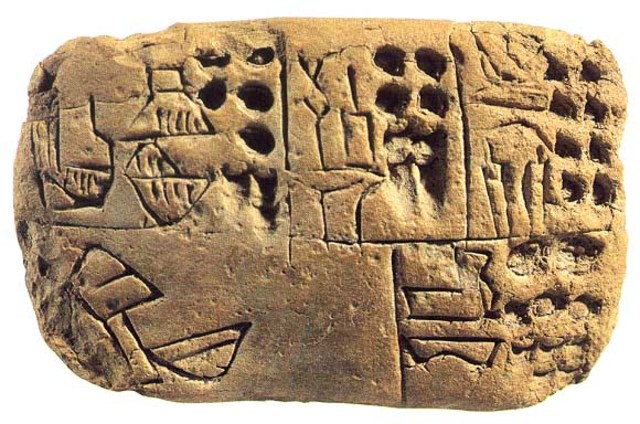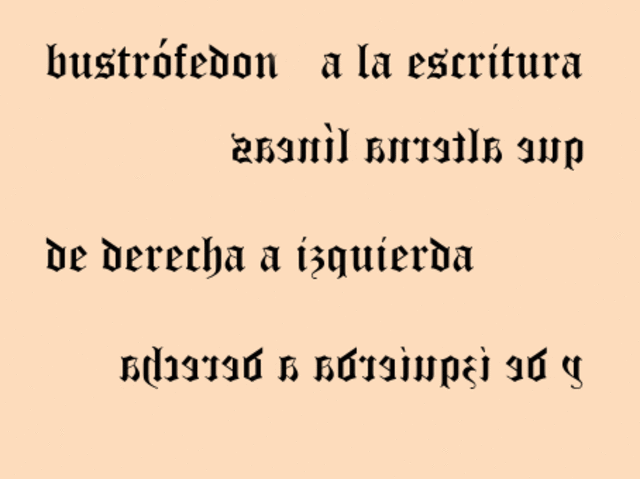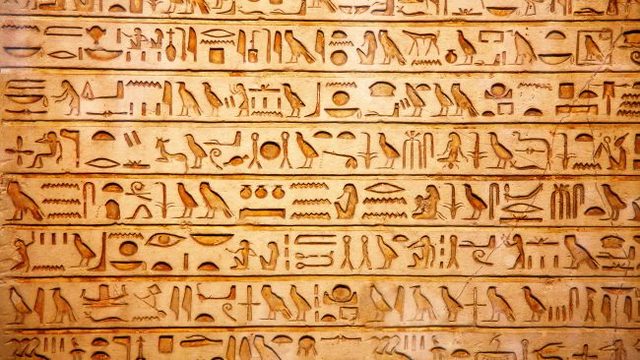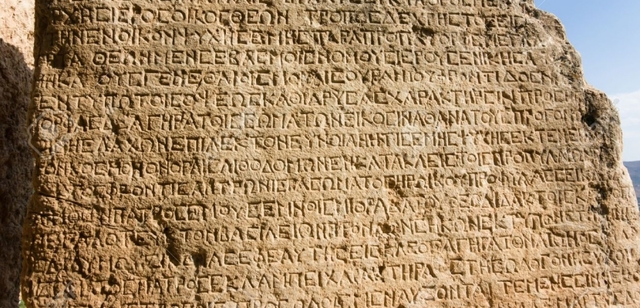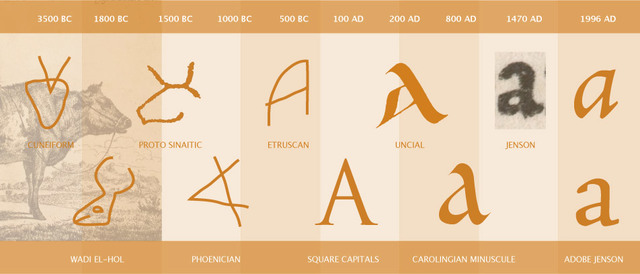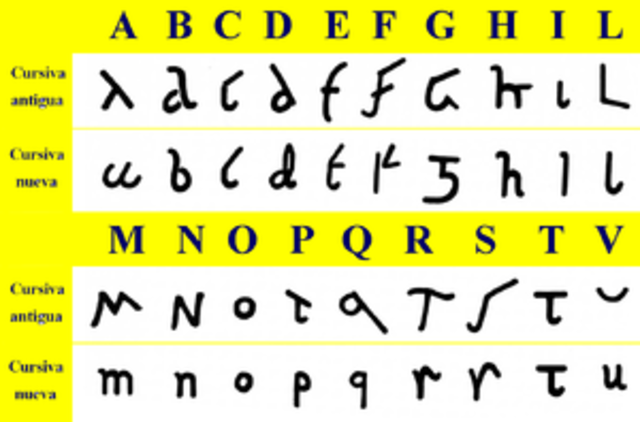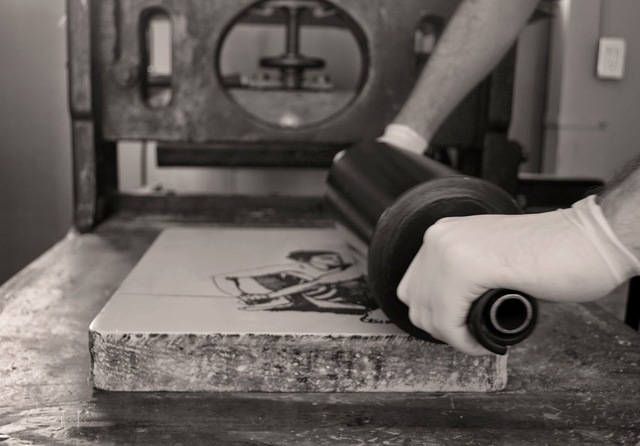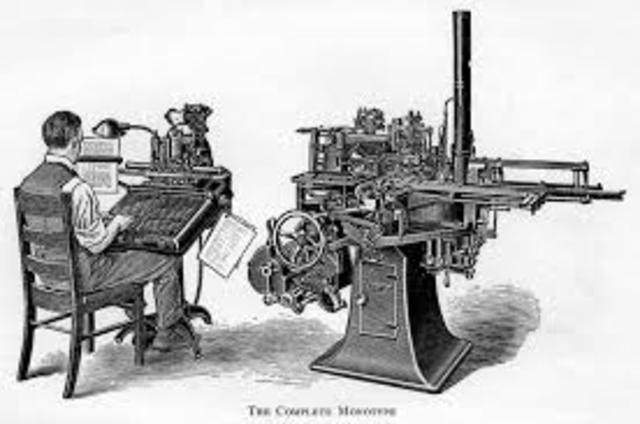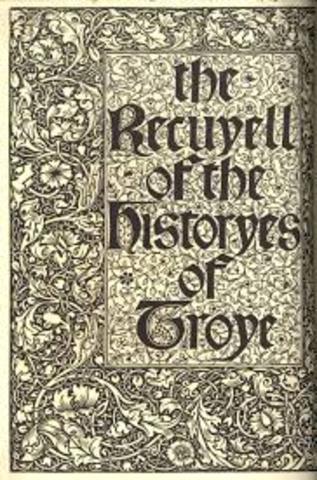
Se basa en pictogramas y se emplea con los incas y los antiguos egipcios. cada pictograma representaba un símbolo. se escribe de derecha a izquierda, se utilizaban ideogramas
se brinda un símbolo a cada palabra, paso palabras abstractas y finalmente quedo como caligrafía del pequeño sello. en el año 1600 impartieron el alfabeto latino.
se relacionaba a escribir columnas inclinadas, pero con el pasar del tiempo se convirtió en una escritura de izquierda a derecha y se cambiaron a los signos. Los escritos cuneiformes desaparecieron en los siglos VI Y VII ac.
La escritura de griega antiguo la escribían en bustrófedon, esta escritura añadió los signos de puntuación lo cual hizo que se desapareciera la escritura de bustrófedon.
Este alfabeto lo utilizaban para la escritura de seis lenguas eslavas, pedro el grande decreto el uso de las letras occidentalizadas y fueron adoptados por el resto de las lenguas y se establece mas 50 lenguas diferentes en Rusia.
se construye con el alfabeto griego y se divulgo por el imperio. Los romanos siempre trataban de emplear siete de sus letras como números básicos porque cada letra representaba un valor numérico.
Consta de 52 letras y 10 números así como símbolos, signos de puntuación y distintas lenguas, las letras de caja baja se inician con las letras mayúsculas.
La transformacion del arameo fue desde el fenicio, el arameo es un lenguaje semitico que se remplazo a finales del VI a.c, suplantado por la escritura hebrea.
Los primeros libros de bloque se imprimieron con un sello de mano y tinta color sepia o gris, que luego sería reemplazada por la tinta negra. Después de imprimir el texto y las ilustraciones, estas se coloreaban a mano con la misma técnica que se aplicaba en los manuscritos góticos.
se imprimió el primer libro en inglés bajo el título de Recuyell of th Historyes of troye del Autot: Raold le Fèvre.
Supuso la fusión del arte y la industria para la
producción de carteles y cromos en color para libros. -
Era un teclado similar al de una barra de escribir con una barra metálica la maquina coloca matrices de latón en una linea y después se difunden.
hace fundición de las letras en plomo y las plasma en una pagina, lo cual le permite la corrección de caracteres individuales.
En el Antiguo Egipto se escribía sobre papiro, un vegetal muy abundante en las riberas del río Nilo (Cyperus papyrus). Fue el primer material que presentaba las propiedades asociadas al papel. En Europa, durante la Edad Media, se utilizó el pergamino, que consistía en pieles de becerros, oveja, cabra o de carnero curtidas con cal y preparadas para recibir la tinta. No obstante este proceso resultaba costoso.
se considera el primer sistema de escritura utilizaban una herramienta en forma de cuña para realizar pictogramas recreados en una tabla de arcilla humeda
Encontramos al destijil: era un movimiento que surge a travez de una revista de theo van, epleaba colores primarios. el constructivismo 1918: nacido en mozcu, se empleaban materiales industriales esto fue primordial para el modernismo. Labauhaus 1919 querían asemejarse mas al diseño después de la 1 guerra se centraron en la funcionalidad que en el adorno. dictaduranazai 1933: Adolfo Hitler promovió el estilo de letra oficial de Alemania En 1941 fue proscrita y sustituida por el tipo romano.